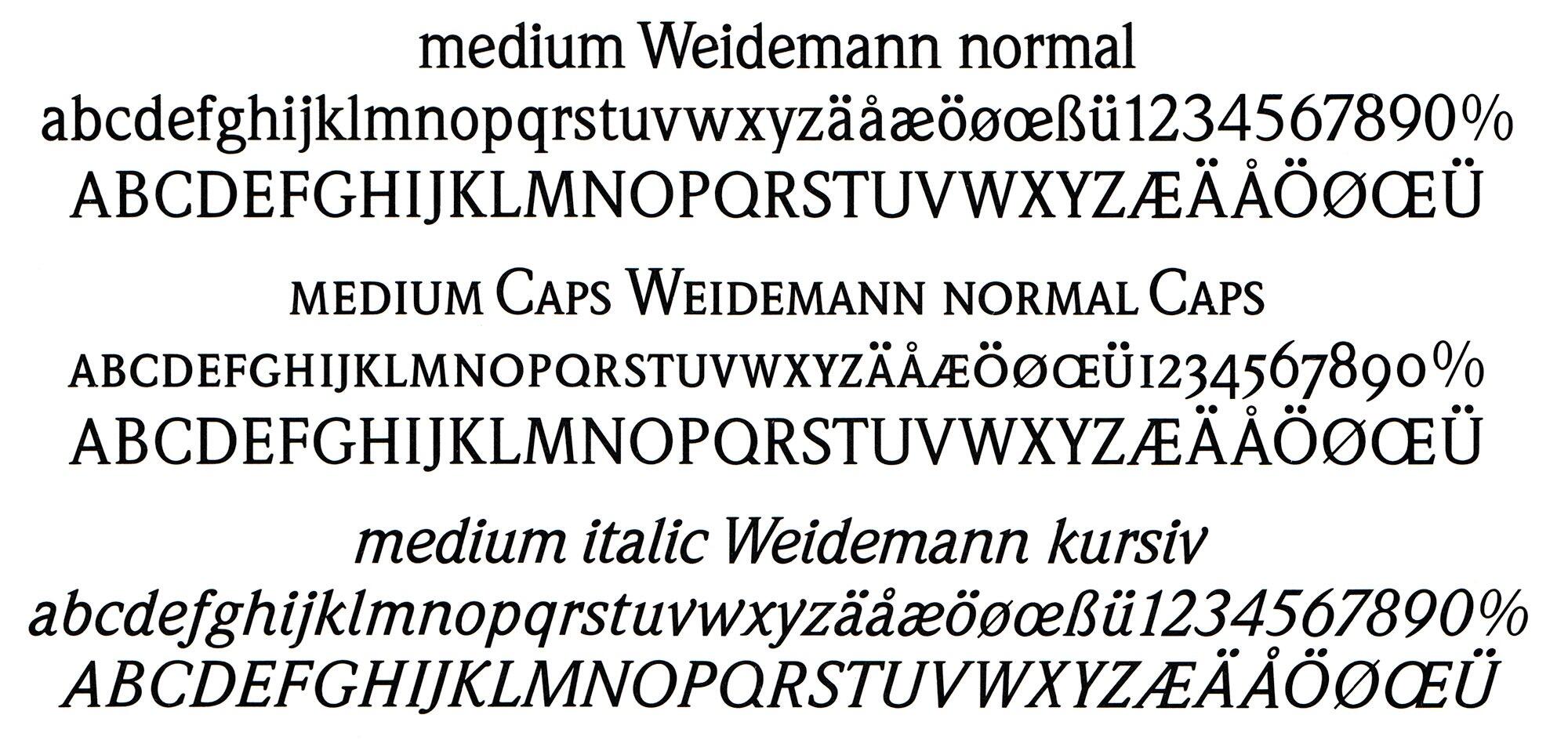
- 1983
- Antiqua humanistisch
Die ITC Weidemann hieß ursprünglich Biblica und entstand für eine konfessionsübergreifende Ausgabe der Bibel durch die Deutsche Bibelgesellschaft. Wegen der Menge des Textes war eine geringe Laufweite unter Beibehaltung guter Leserlichkeit gefordert. Daher erscheinen die Buchstaben einerseits so schmal, verlieren aber wegen der kräftigen Serifen auch in kleinen Größen nicht ihre wesentlichen Erkennungsmerkmale.
Für die Veröffentlichung bei ITC wurde die Schrift in Zusammenarbeit mit Kurt Strecker auf 8 Schnitte ausgebaut.